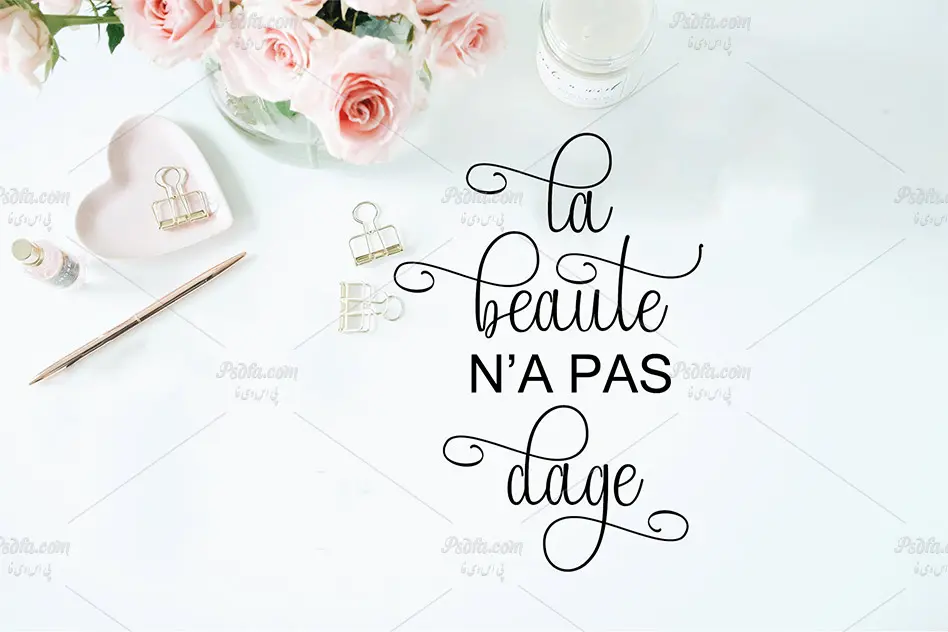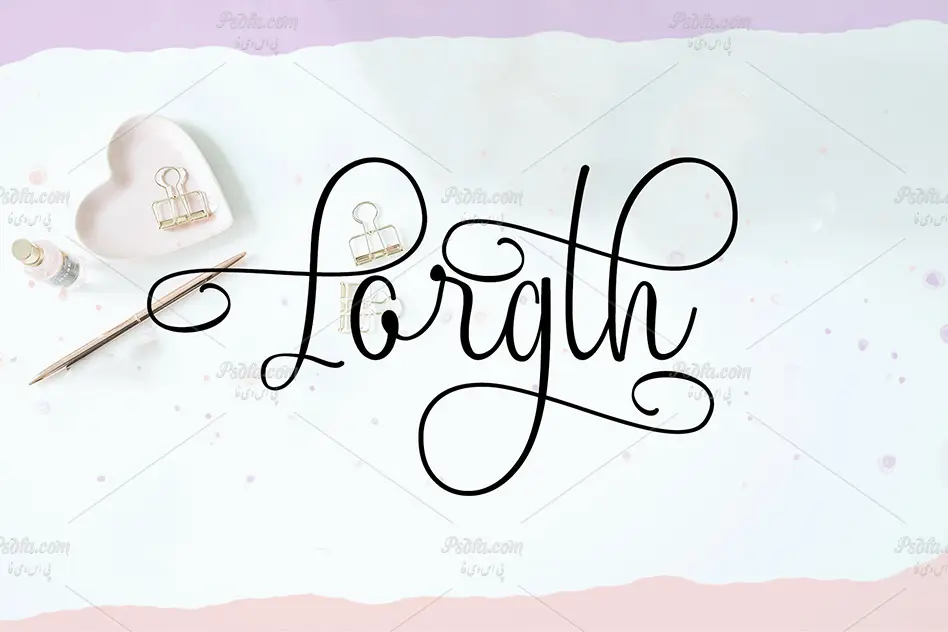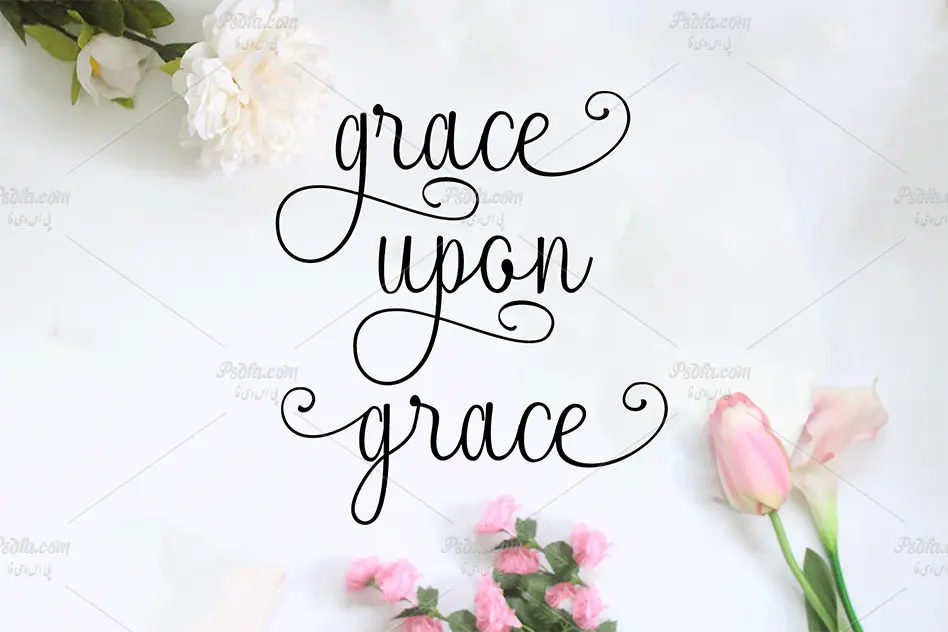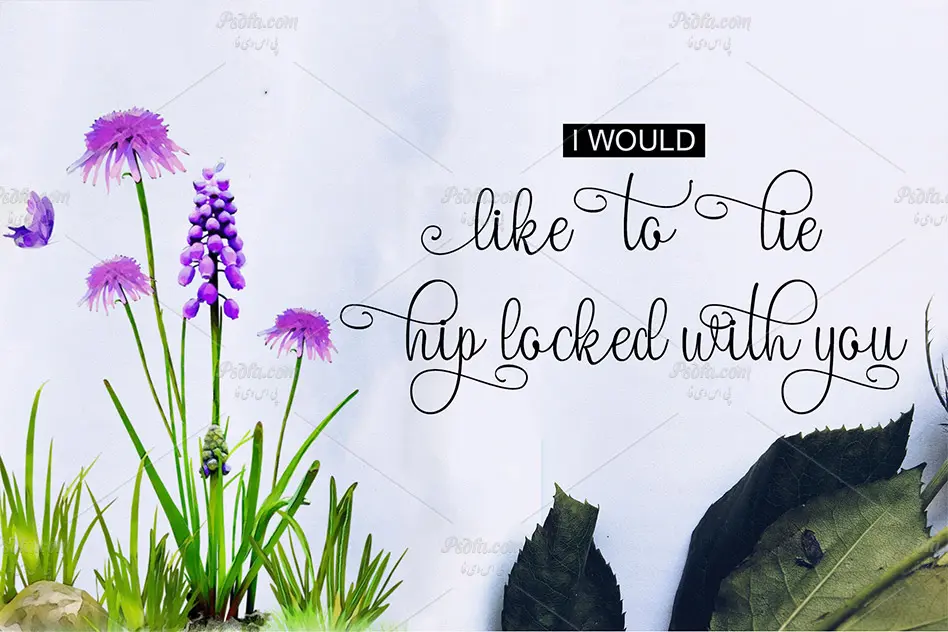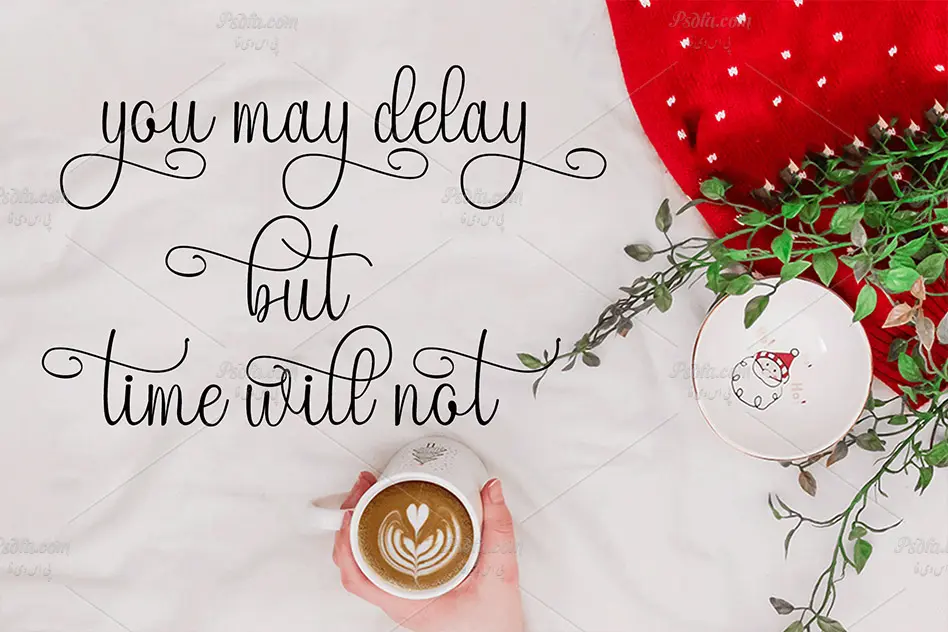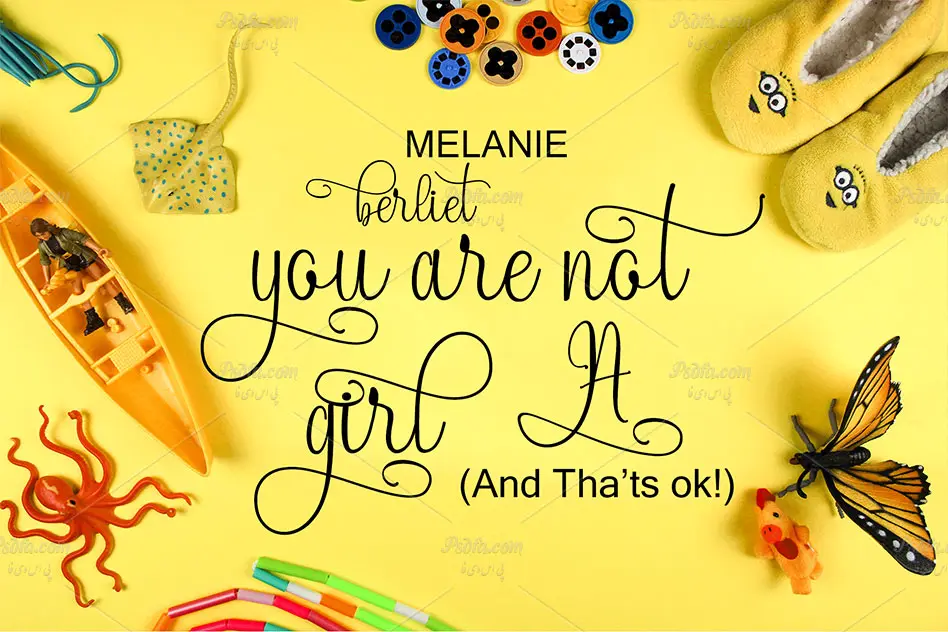
اسکریپت فونت انگلیسی Lazortha یک قلم دستنویس لاتین است که میتوان از آن در طرحهای گرافیکی به خصوص طراحی انواع کارت تبریک و کارت پستال استفاده نمود. این فونت زیبا در قالب 2 فایل ttf, otf بر روی سایت بارگذاری شده است که پس از نصب یکی از این دو فرمت در شاخه فونتهای سیستم قادر به استفاده از آن در تمام نرمافزارهای گرافیکی خواهید بود. فونت Lazortha در وزن معمولی (Regular) طراحی شده است که مناسب جهت استفاده در طرحهای گرافیکی همچون انواع کارت تبریک، کارت پستال، کارت ویزیت، طراحی انواع پوستر، بروشور، طراحی بر روی بستهبندی محصولات، طراحی قاب عکس و دیگر طرحهای گرافیکی مورد استفاده قرار داد.
- نام فونت : Lazortha
- وزن : معمولی (Regular)